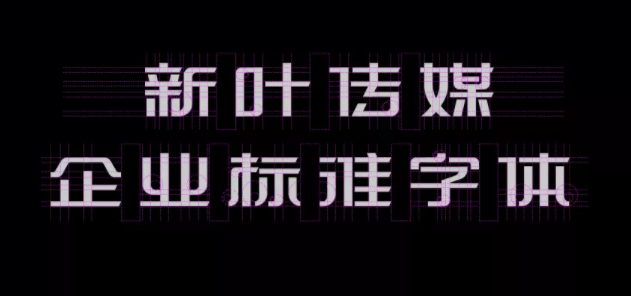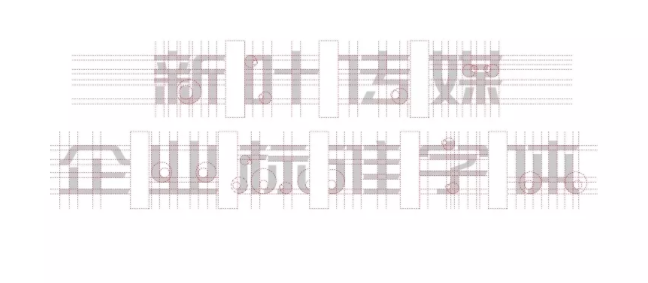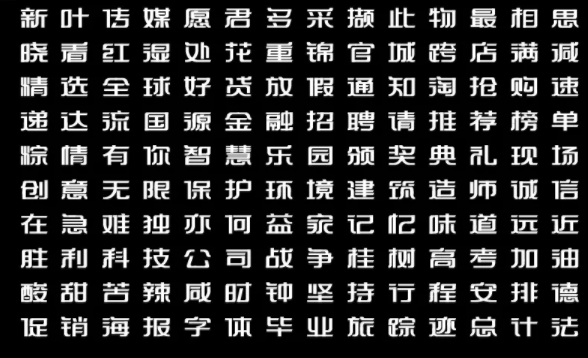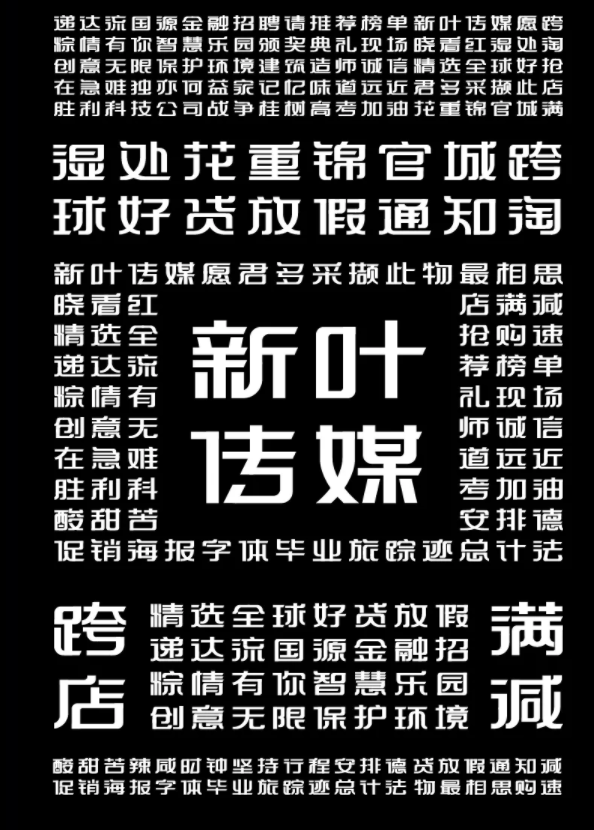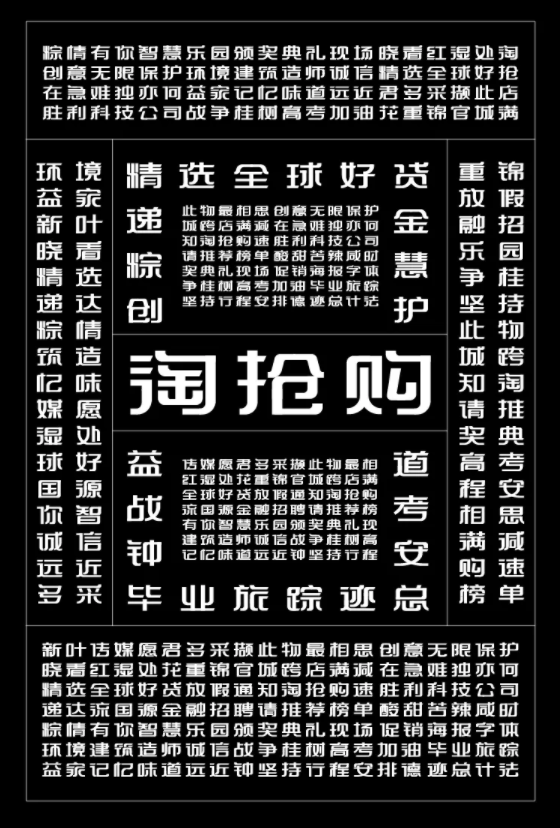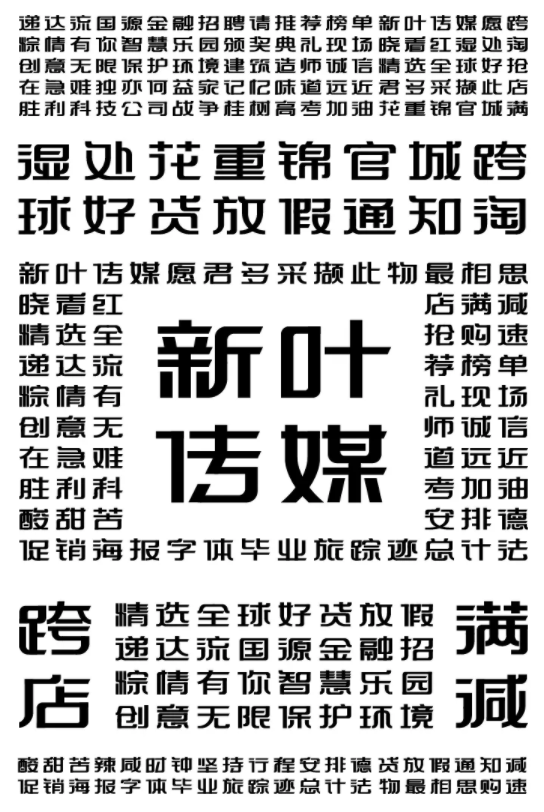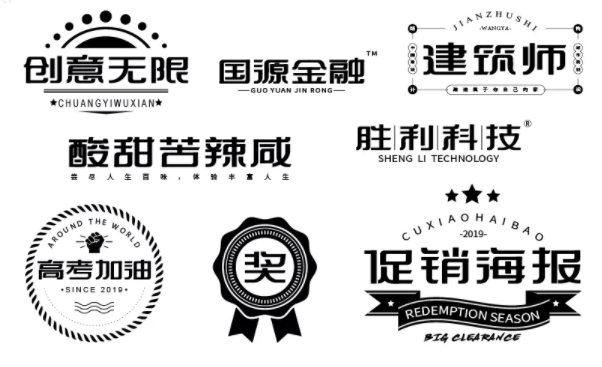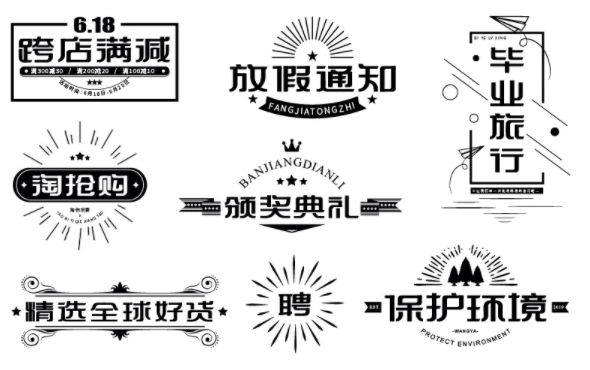
新叶企标体,字体预告
字体名称新叶企标体项目顾问乔建设计与开发指导王亚、袁立风格现代、力量 、大气、动感
适用范围企业标准字、海报、广告设计、影视动态等
这是一款所有企业都可以直接用做企业标准字的商业字库。字体稳重大方,方中带圆,圆中有方,整体笔画均匀美观,可直接用作企业LOGO的标准字体。
细节方面,横的笔画右侧做了一个斜角处理,充满动感,打破了基本字形的拘束感。整个字形中带着一种严谨,但又不失风趣,整体风格上突破了基本字体的固定模式。